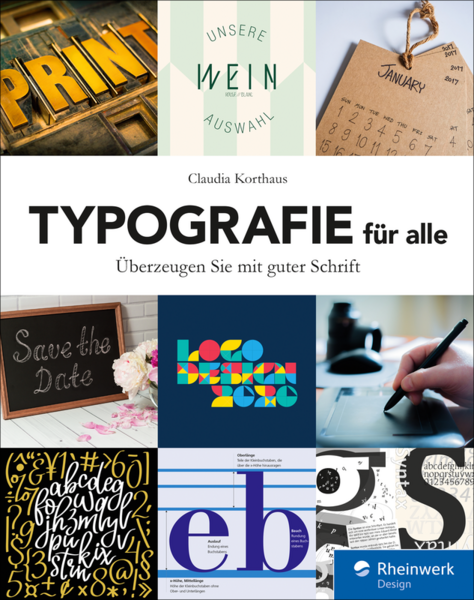
Das Buch »Typografie für alle: Überzeugen Sie mit guter Schrift« ist ein Typografie-Buch von Claudia Korthaus, das sich ausdrücklich an »Nicht-Designer« richtet. Der Klappentext nennt als Beispiele Autoren, Wissenschaftler, Anwälte, Sekretäre und Studenten, die überzeugende Dokumente, Präsentationen, Geschäftsberichte, Werbemittel und Websites gestalten möchten. Entsprechend versucht das Buch Grundlagen des Grafikdesigns, insbesondere im Hinblick auf die Schriftanwendung, zu vermitteln.
Die 257 Seiten des durchgängig vollfarbigen Buches gliedern sich dabei in vier Kapitel. Das erste Kapitel erklärt kurz grundlegendes zur Bedeutung der Typografie in gestalterischer Arbeit. Kapitel 2 (»Die Schrift als Schlüssel«) gibt einen Überblick, wo man kommerzielle und kostenlose Schriften herbekommt und was es in Hinblick auf die Qualität dabei zu beachten gibt. In Kapitel 3 folgen »Schriftwahl und Schriftmischung«. Ausgehend von einer Schriftkategorisierung mit sechs »Schubladen« werden typische gestalterische Schrifteigenschaften und mögliche Anwendungen besprochen. Thematisiert werden hier auch Details zur Lesbarkeit von Schrift und Prinzipien der Schriftmischung.
Mit über 100 Seiten nimmt Kapitel 4 (»Die Praxis«) den größten Teil des Buches ein. Neben Erklärungen zur Detailtypografie erfolgt die Vermittlung des Wissens hier beispielhaft an konkreten Projekten:
Einladung zur Taufe, Die Visitenkarte eines Geigers, Das Geschäftspapier eines Rollerverleihs, Die Broschüre eines Reisebüros, Eine Bachelorarbeit, Die Website eines Gewürzanbieters, Ein Geschäftsbericht.
Beispielhafte Gestaltungen als Positiv- und Negativbeispiele vermitteln hier anschaulich, worauf Laien bei der Gestaltung achten sollten.
Die Vermittlung der Grundlagen von Gestaltung und Typografie an »Nicht-Designer« in einem einzelnen Buch ist eine herausfordernde, nur schwer lösbare Aufgabe. Es gibt einen Grund, warum Grafikdesigner ein Beruf ist, der in mehrjährigen Berufsausbildungen bzw. Studiengängen vermittelt wird. Es gibt umfassendes Wissen zu vermitteln und erst im Gesamtzusammenhang kann alles in guter Gestaltung münden. So versucht das Buch vielleicht ein bisschen zu viel und spannt den Bogen zu weit. Der Ansatz, gute und schlechte Gestaltungsbeispiele vollfarbig gegenüberzustellen, ist für Laien sicherlich ein gut gewählter, anschaulicher Weg. Hier kann man einiges Lernen und auch die Grundlagen zu Schriftklassifikation und Detailtypografie schaden freilich nicht. Letztlich zeigen die Gestaltungsbeispiele aber dann doch klassische Grafikdesigner-Arbeiten. Dafür muss man professionelle Satzprogramme wie InDesign besitzen und natürlich beherrschen, um etwa die gezeigten Gestaltungsraster überhaupt auch nur anlegen bzw. sinnvoll nutzen zu können. Ganz zu schweigen vom Webdesign, was wieder einen eigenen Fachbereich bildet. So müssen Käufer des Buches, die tatsächlich Laien sind, dann wohl doch noch eine ganze Menge anderer Bücher mit in den Warenkorb legen, um das gelernte Wissen überhaupt in die Praxis umsetzen zu können.
Und grundsätzlich würde ich mir wünschen, dass alle Fachbücher dieser Art nicht nur ein Textkorrektorat durchlaufen, sondern auch von Fachleuten noch einmal vor Drucklegung gegengelesen werden. So mancher fachliche Fehler, der von Verlag und Textkorrektorat nicht bemerkt wird, spränge Fachleuten leicht ins Auge.
Untertitel: Überzeugen Sie mit guter Schrift